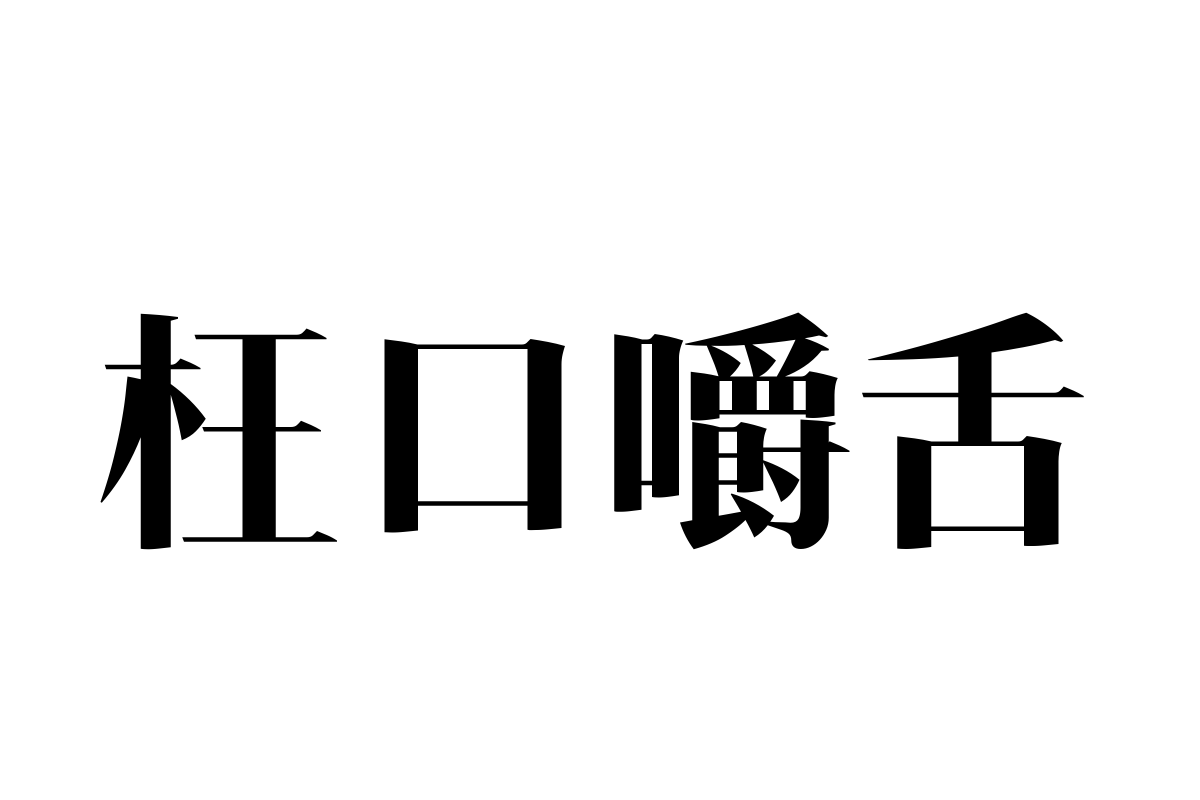
汉仪瑞意宋_80W是一款现代而优雅的中文字体。这款字体的设计灵感来源于中国传统文化,融合了古典与现代的元素,展现出独特的韵味和风格。
字体特点:
1. 字形结构:汉仪瑞意宋_80W采用了简洁而流畅的线条,使得文字看起来既清晰又美观。每个字的结构都经过精心设计,使得整体效果和谐统一。
2. 笔画细节:这款字体在笔画的处理上非常细致,无论是横、竖、撇、捺等基本笔画,还是一些复杂的组合笔画,都能保持清晰的轮廓和准确的间距。这使得文字在阅读时更加舒适,不易产生视觉疲劳。
3. 字重感:汉仪瑞意宋_80W的字重感适中,既不过于厚重,也不过于轻盈。这种平衡使得文字在视觉上既具有力量感,又不失柔和。
4. 适应性:这款字体适用于多种应用场景,包括书籍、杂志、广告、网页等。无论是正式的文件还是轻松的日常应用,汉仪瑞意宋_80W都能提供良好的视觉效果。
总之,汉仪瑞意宋_80W是一款非常适合现代设计需求的中文字体,无论是用于商业还是艺术领域,都能展现出其独特的魅力。